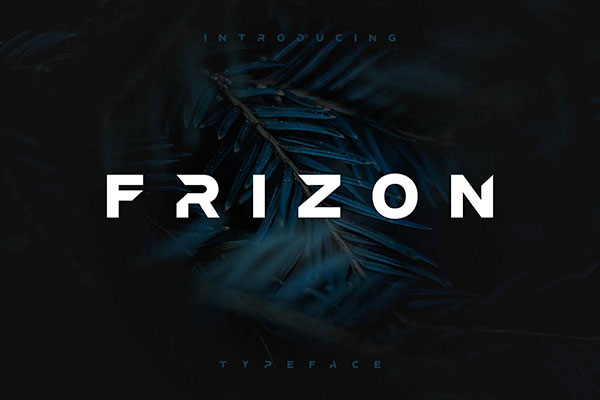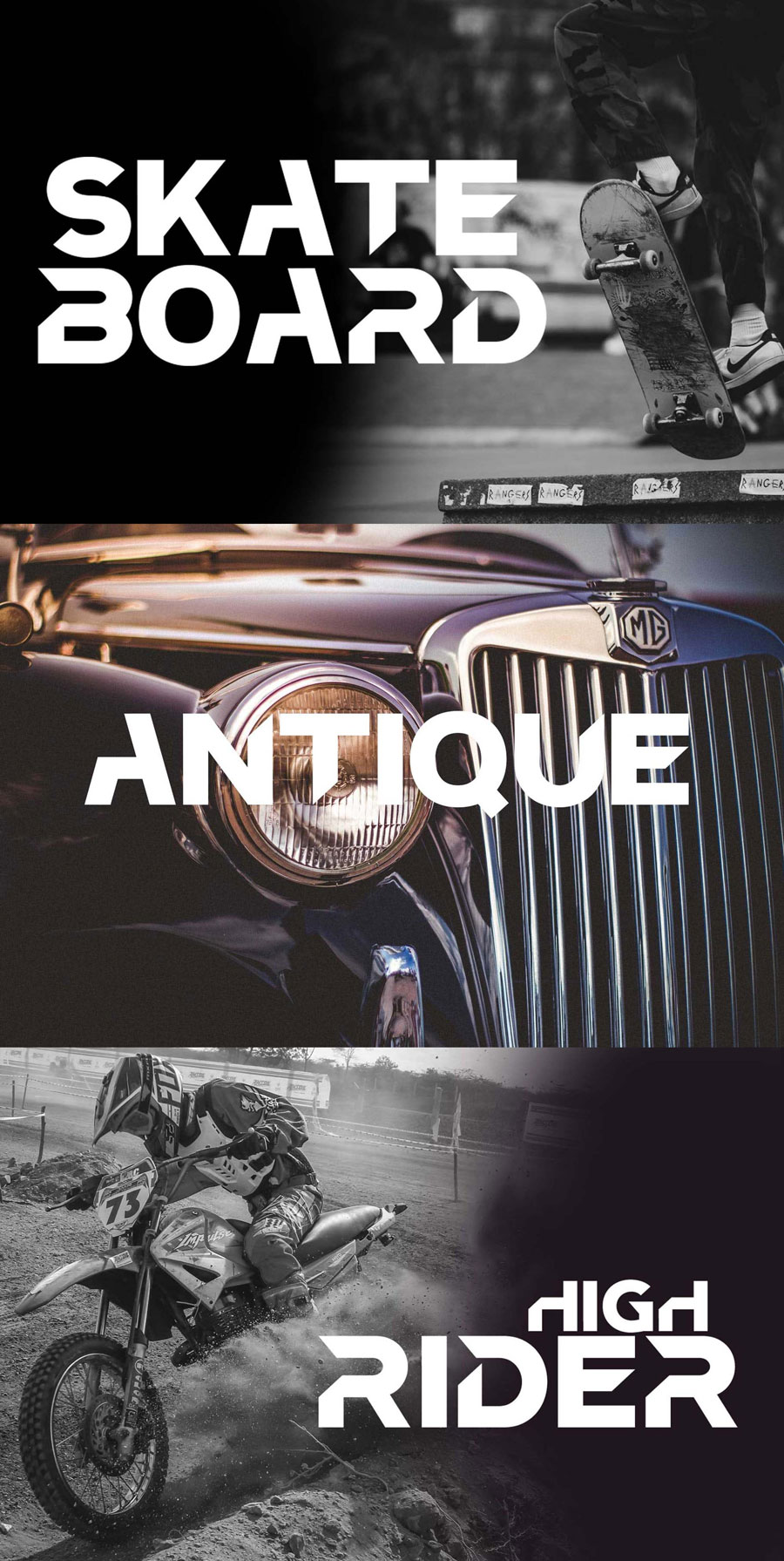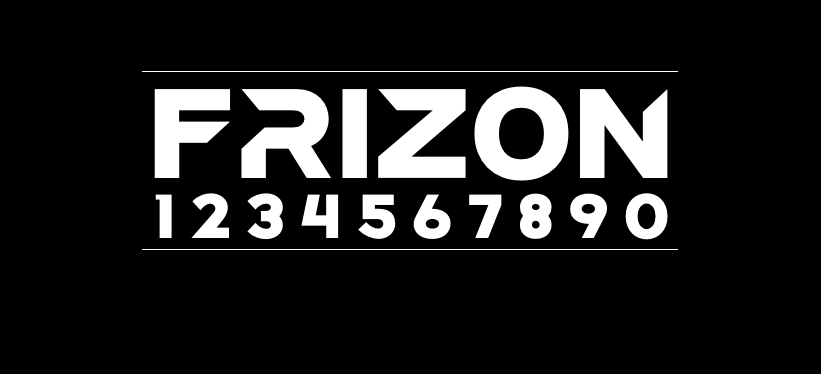
Frizon
Frizon字体介绍
Frizon是美国Unblast团队精心打造推出的一款英文字体。
Frizon是一种抽象的显示字体,有一组壮观的大写字母,数字和符号。具有锐利边缘的字符也显示出惊人的异常,这种异常可以在字母R,A,H和T的特殊几何设计中注意到。这种粗体可以添加到品牌和包装设计,徽标,标语中适用于社交媒体平台和网站,广告,海报,服装设计,标题以及许多其他项目。与经典字体(例如Arial和Helvetica)一起使用时,配对此字体应能充分利用它。
Frizon字体应用示例